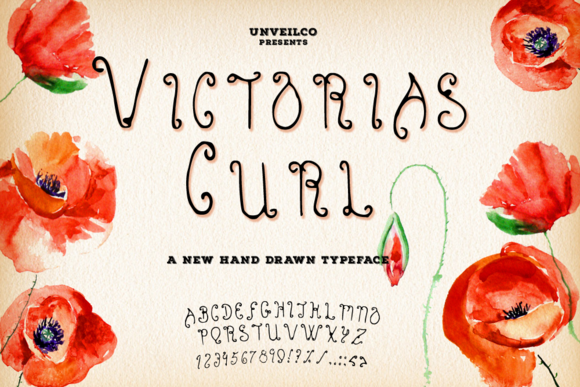
Victoria’s Curl Typeface – Download Grátis
A Victoria’s Curl Typeface é uma elegante e leve tipografia perfeita para quem valoriza delicadeza e charme. Inspirada no estilo vitoriano, ela permite que você faça um impressionante salto ao criar designs vintage ou retro como flyers, logos, nomes de marca, etiquetas e muito mais — tudo com um toque romântico e sofisticado. Com sua aparência delicada, essa fonte faz um contraponto perfeito a qualquer tipo de texto, tornando-a uma escolha ideal para aqueles que desejam criar algo singelamente encantador. Seja você criando uma campanha de marketing ou simplesmente decorando o layout de seu próximo projeto gráfico, Victoria’s Curl é sua fonte perfeita. Com Victoria’s Curl na sua mesa, você pode explorar a diversidade do design vintage sem sair da sua confortável sala de trabalho. Esta fonte é mais que um recurso gráfico; ela é uma pequena caixa de encantamento para seus projetos — pronta para ajudá-lo a fazer sua marca se destacar.